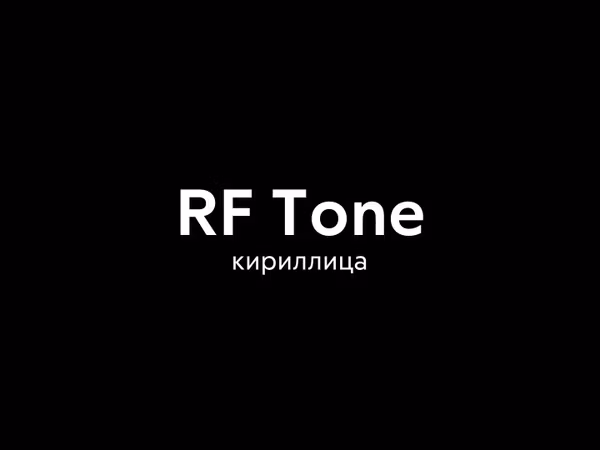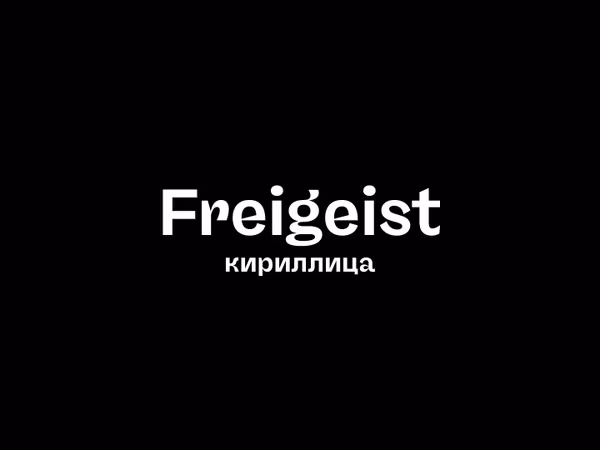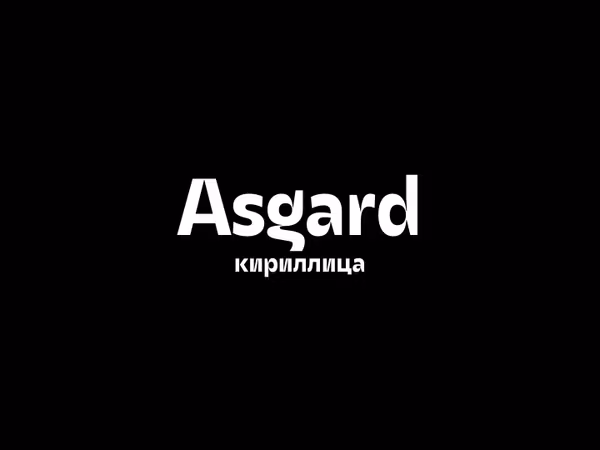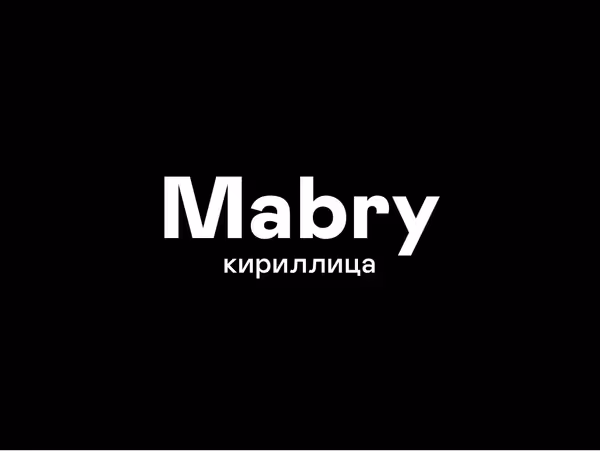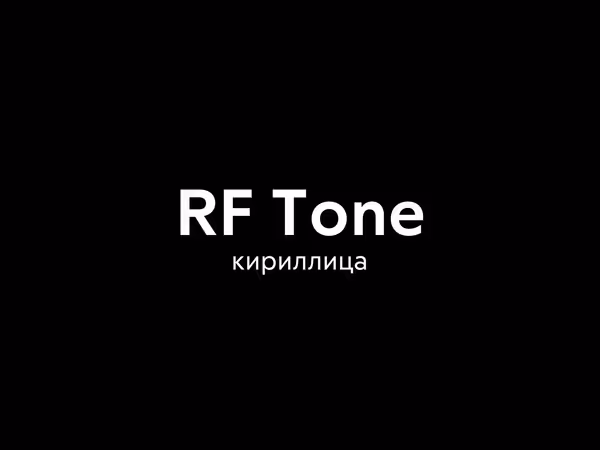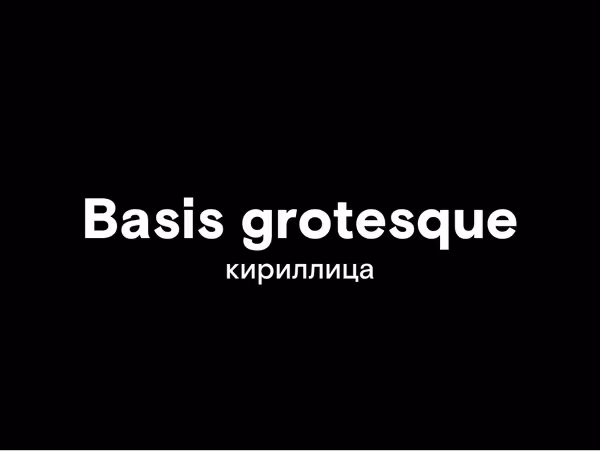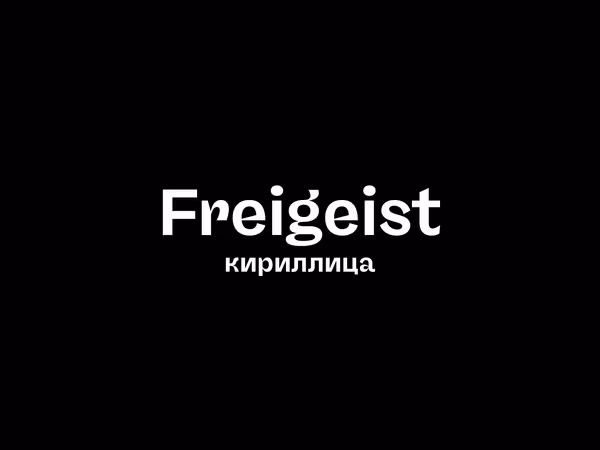
Codec Cold & Warm шрифт
Codec Warm / Cold - это геометрическая система кириллический шрифтов без засечек. Как и во многих современных шрифтах, вдохновленных конструкционистской логикой Futura, дизайн определяется небольшим выбором между строгим геометрическим совершенством и минимальными гуманистическими исправлениями.
Asgard шрифт
Asgard - кириллический SansSerif шрифт от FRANCESCO CANOVARO. Cуперсемейство из 9 стилей по 8 весов, всего 72 шрифта, каждый поставляется с расширенным набором из 968 символов, охватывающих более 200 языков с использованием латинского, греческого и кириллического шрифтов.
Freigeist шрифт
Freigeist - это суперсемейство кириллических гротесков. Он отражает неприрученный и выразительный дух ранних шрифтов без засечек 19 века и помещает их в современный контекст, в результате чего получается многогранное семейство с широким спектром стилей шрифтов и функций для современного набора.
RF Tone шрифт
Шрифт RF Tone удобен для чтения отлично подходит в качестве основного шрифта в дизайне веб-сайтов. Логотипы и брендинг, упаковка, плакаты, музыкальные обложки, видео - это лишь некоторые области, в которых Tone может вам помочь.
Basis Grotesque Pro шрифт
Basis Grotesque - это классический, строгий и современный кириллический шрифт без засечек, разработанный Энтони Шеретом и Эддом Харрингтоном из Colophon Foundry. Отлично подходящий для веб-сайтов, интерфейсов и брендинга.
Mabry Pro шрифт
Кириллический шрифт Mabry Pro - это классический с одной стороны и современный шрифт с другой стороны. Одновременно изысканный и грубый. Необычный, красивый и свежий шрифт для ваших современных проектов.